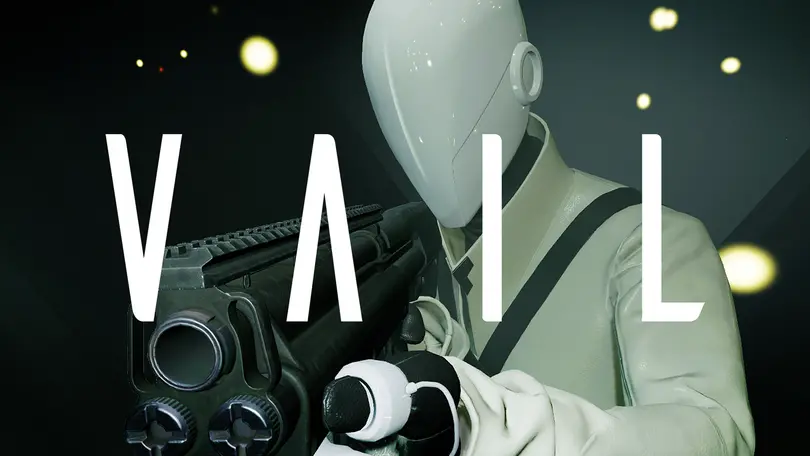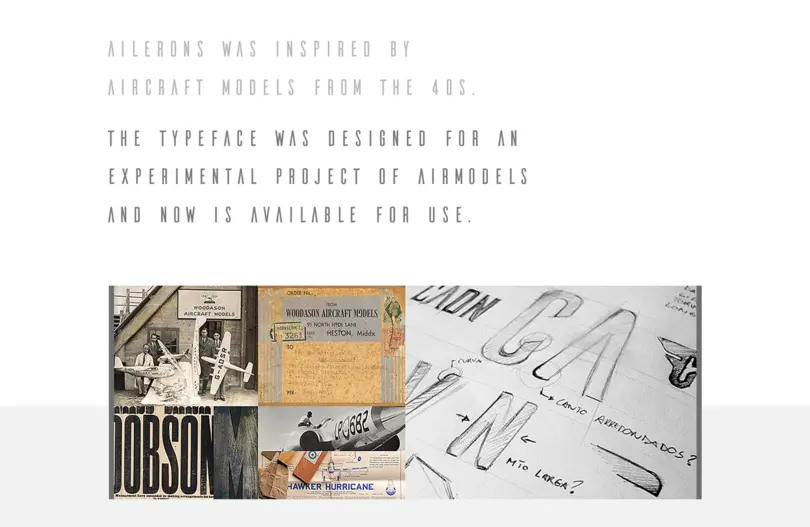
Design por teste: criando conexões significativas em mundos virtuais.
“ É um momento emocionante para trabalhar nessa área. Há muito espaço para inovação e mudança de paradigma de como experimentar tudo, desde música, jogos, entretenimento até experiências sociais. ”
Elizabeth Ann Clark.
Em uma época em que muitos de nós nos sentimos mais distantes uns dos outros do que nunca, softwares como Zoom, FaceTime, transmissões ao vivo e videogames online substituíram a socialização pessoal. A realidade virtual também teve um aumento no uso e, para muitas pessoas, entrar em um jogo virtual com outros jogadores pode fornecer uma camada adicional de interatividade (veja: toque fantasma) que não pode ser alcançada com outras mídias.
Já há algum tempo que observamos o espaço de RV com um interesse particular em como a fonte é usada em ambientes virtuais.
“É um momento emocionante para trabalhar nessa área. Há muito espaço para inovação e mudança de paradigma de como experimentar tudo, desde música, jogos, entretenimento até experiências sociais”, diz Elizabeth Ann Clark, Diretora Criativa da desenvolvedora de jogos de RV AEXLAB.
Clark supervisiona a estética visual do AEXLAB e de seu principal jogo de realidade virtual, VAIL, gerenciando uma equipe de designers visuais, artistas e artistas conceituais, artistas técnicos, artistas de personagens e artistas ambientais. A AEXLAB já criou experiências de RV para a Red Bull, o Instituto Americano de Arquitetos e a Epic Games.
Em 2015, Clark começou a projetar para RV de forma um tanto involuntária. Tradicionalmente formada como cineasta, ela estava trabalhando em um projeto de jogo chamado Water Planet para um álbum que ela havia produzido quando alguém sugeriu que ela deveria transformá-lo em RV. O que começou como um projeto musical evoluiu para o cinema e, finalmente, para a realidade virtual, e acabou chegando ao Instituto de Arte Contemporânea de Miami.
Na época, não havia muitos recursos para designers e desenvolvedores de RV iniciantes, então Clark e seu parceiro e CTO da AEXLAB, Albert Ovadia, contaram com o Unreal Dev Grants Program, uma pequena mas crescente comunidade de RV, e horas de testes.
“Você pode tentar fazer escolhas de design semelhantes às que faria ao abordar outras mídias”, diz Clark, “mas os mesmos princípios nem sempre se aplicam à RV, por isso tem sido uma jornada interessante explorar como apresentar informações em mundos virtuais”. Ao projetar para RV em comparação com um espaço 2D, por exemplo, há muito mais espaço para cobrir porque os jogadores têm uma visão completa de 360 graus e podem explorar cada centímetro do ambiente com grande detalhe. A outra peça importante a considerar ao projetar um jogo de RV é a interface.
“ Você pode tentar fazer escolhas de design semelhantes às que faria ao abordar outras mídias, mas os mesmos princípios nem sempre se aplicam à RV, por isso tem sido uma jornada interessante explorar como apresentar informações em mundos virtuais. ”
Elizabeth Ann Clark.
Quando se trata de texto, Clark aponta a quantidade de ajustes necessários para acertar na RV. A AEXLAB trabalha duro para garantir que o texto nos menus e minimapas da experiência VAIL seja confortável e possa ser personalizado de acordo com as preferências do jogador. “Na VR você realmente precisa experimentar o que é confortável”, Clark observa: “Dependendo da localização, tamanho ou qualidade de uma fonte, ela pode realmente ter um substancial efeito na experiência. Se for mal feito, também pode contribuir para o enjôo, por isso é experimental. Não há documentação para o melhor caso de uso no momento, então é algo que ainda está sendo desenvolvido. Há muita informação gratuita disponível, mas acho que ainda há muito espaço para melhorias no design e isso é algo que veremos desenvolver muito nos próximos anos.”
VAIL Game Cover Art
Sua equipe também teve muito cuidado ao selecionar a fonte do VAIL. O CTO da AEXLAB, Ovadia, encontrou a fonte do jogo, ailerons, que na verdade era a tese final de um designer brasileiro enquanto estudava design gráfico. O jogo se passa em um futuro próximo, em uma Terra pós-apocalíptica com uma colônia em órbita que promete uma nova fase da vida. Visualmente, o jogo tem uma linguagem de design minimalista com tons principalmente monocromáticos e detalhes em cores neon, além de um tema futurista de ficção científica. A fonte precisava se adequar a essa estética e ao mesmo tempo funcionar bem na experiência de RV, e os ailerons fizeram bem o trabalho.
“Eu realmente me apaixonei pelos ailerons, ao ler mais sobre o designer e suas escolhas ao projetá-lo. É lindo porque um aileron é a parte da mecânica de como as asas de um avião se abrem e se movem.”
O designer de fontes, Adilson Gonzalez, foi inspirado pelas aeronaves da década de 1940, o que fica evidente no design arejado acentuado com um toque de ficção científica. Clark também é apaixonada por apoiar jovens designers e menciona que um de seus recursos favoritos é a biblioteca de fontes Typelab, que apresenta fontes produzidas por jovens artistas em todo o mundo.
Na frente estética geral, Clark fala sobre sua amostra Pantone favorita, um verde-limão neon. “Atualmente estou obcecado por #C0FF00, é meu tom de verde favorito e literalmente não consigo parar de usá-lo, estou quase começando a me preocupar se estou abusando dele.” Os designs iniciais de VAIL eram muito monocromáticos, mas a equipe lentamente trouxe mais cor ao jogo – algo que Clark acredita que tornará o jogo mais amigável e possivelmente mais atraente para um público mais amplo.
“Ter acesso às ferramentas do Unreal Engine abriu mundos para mim, para poder criar meu próprio universo. É realmente um momento mágico para começar.”
Para aqueles interessados em aprender mais sobre design para RV, Clark recomenda baixar o Unreal Engine e conferir seus tutoriais educacionais gratuitos, minicursos, podcasts e transmissões ao vivo no YouTube.